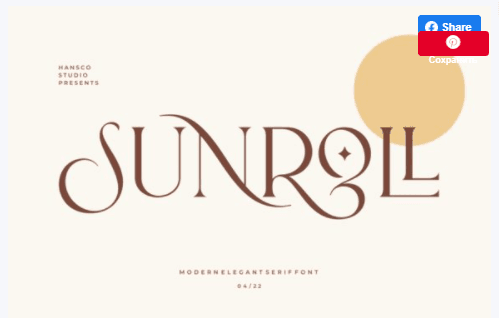
Sunroll Font
Sunroll - это тонкий буквенный шрифт с деликатными засечками. Этот шрифт имеет кодировку PUA, что означает, что вы можете легко получить доступ ко всем глифам и росчеркам!
Влюбитесь в его невероятно универсальный стиль и используйте его для создания впечатляющих дизайнов!